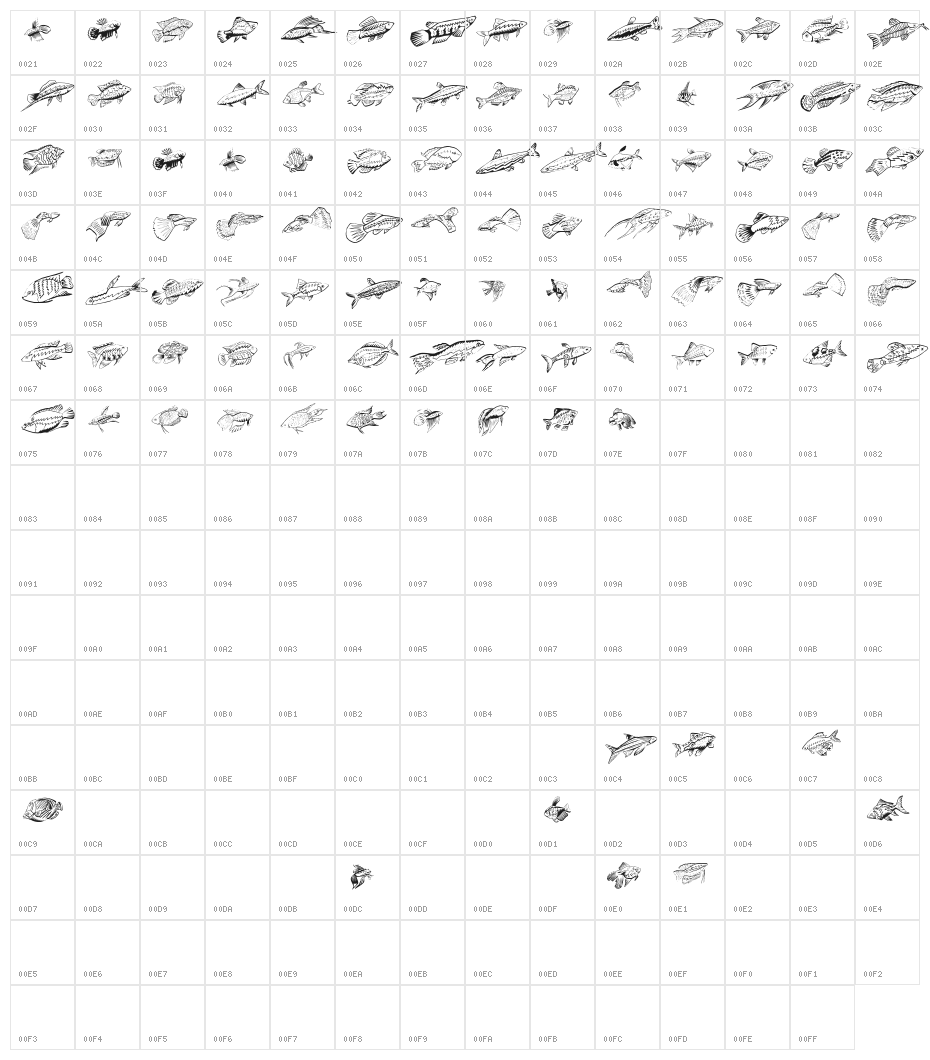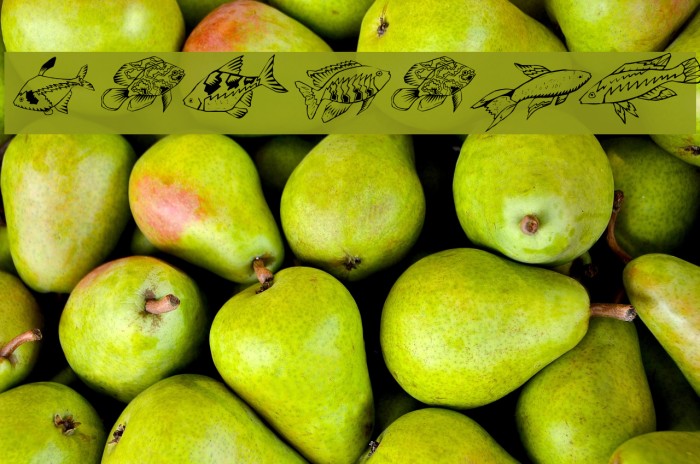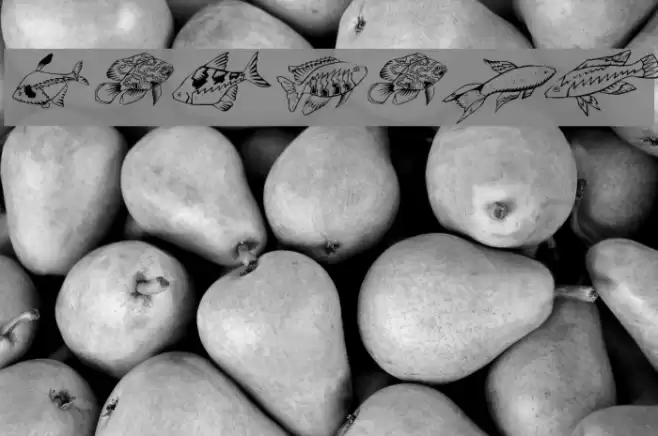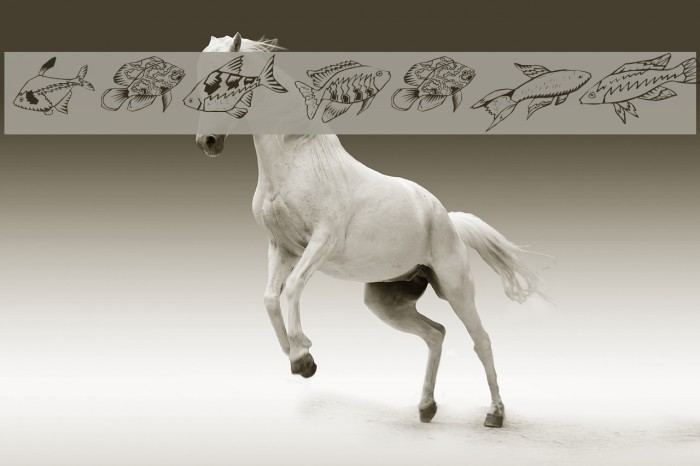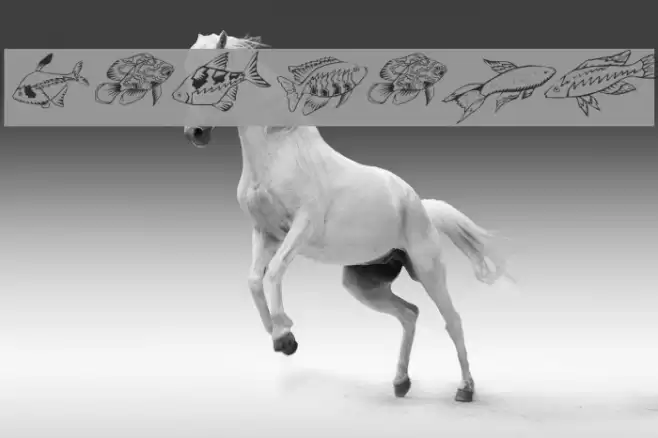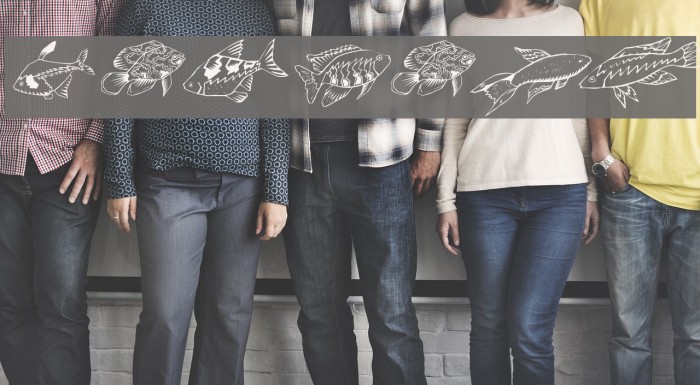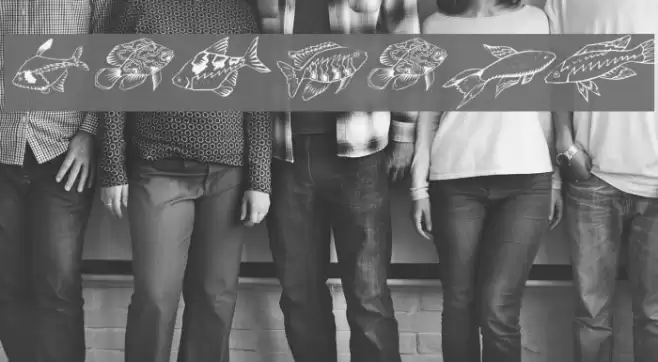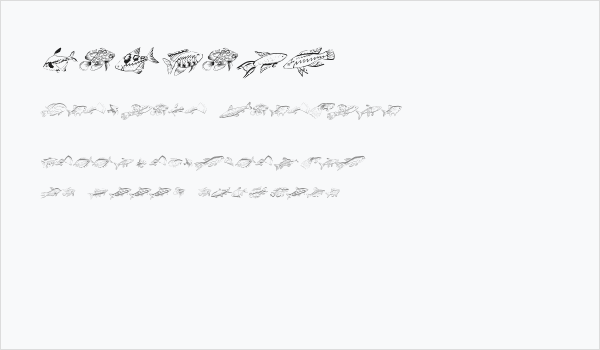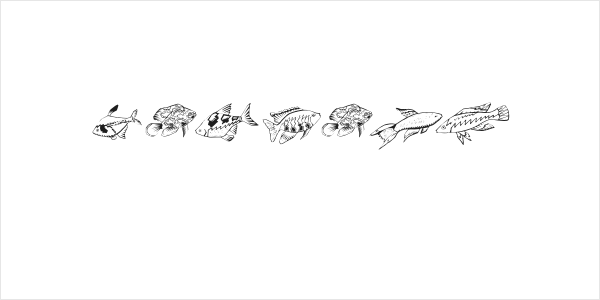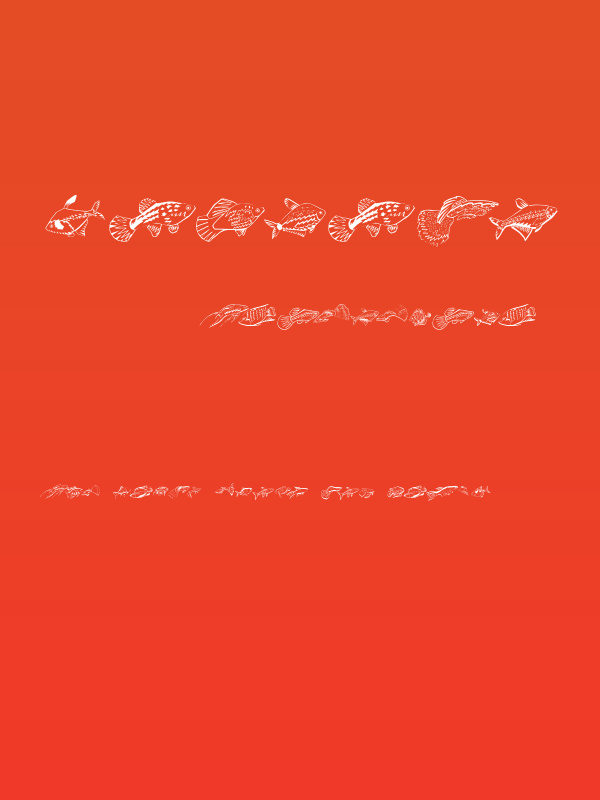
Fishing Font
| Общий стиль | Decorative, Whimsical, Hand-drawn |
| Область применения | Logos, Headlines, Posters, Themed invitations |
| Рекомендуемые проекты | Children's books, aquarium branding, fishing event posters, educational materials, playful packaging. |